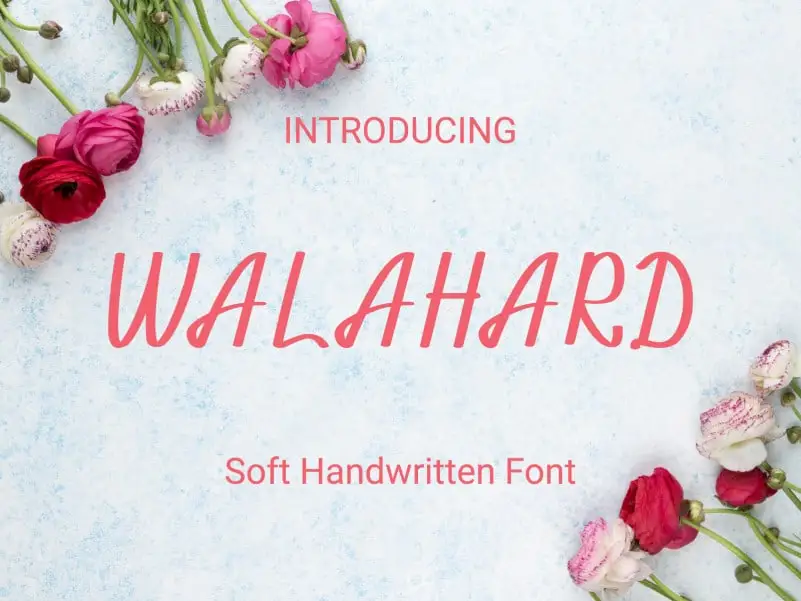
Walahard Script Font – Download Grátis
Introduzimos Walahard Script Font, uma elegante e suave fonte escrita à mão. Ela captura a autenticidade única do estilo para oferecer inspiração criativa aos designers de todos os níveis. Perfeita para criar cartões de aniversário adoráveis, postais bonitos e até mesmo cartas de casamento elegantes. Sua suavidade e naturalidade são ideais para tornar seus trabalhos especiais ainda mais memoráveis na Web e nas redes sociais. Seja para cartazes de casamentos ou cartões personalizados, Walahard Script é uma fonte perfeita para quem busca estilo original e confortável para suas criações.